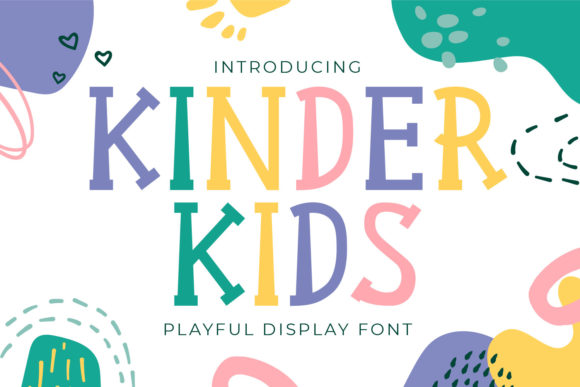
Kinder Kids
Review Completo da Fonte “Kinder Kids”: A Escolha Perfeita para Projetos Infantiles
Se você está procurando uma tipografia que transmita diversão, alegria e cuteness, a Kinder Kids chega como a solução ideal. Desenvolvida para ser playful e cute, essa fonte display se destaca em projetos que envolvem cartoons, jogos infantis e qualquer criação que precise de um toque delicado e encantador.
Principais Características da Kinder Kids
- Design divertido e amigável – Cada letra possui traços arredondados e espaçados, facilitando a leitura para crianças.
- Versatilidade – Ideal para capas de livros infantis, interfaces de jogos, convites de festas e materiais de marketing voltados ao público infantil.
- Alta legibilidade – Apesar do estilo lúdico, a fonte mantém clareza mesmo em tamanhos pequenos.
Por que escolher a Kinder Kids?
Ao escolher a Kinder Kids, você garante:
- Um visual cativante que atrai a atenção de crianças e pais.
- Coerência visual em toda a identidade visual de produtos voltados ao público infantil.
- Facilidade de integração em layouts digitais e impressos, reduzindo tempo de produção.
Aplicações Práticas
- Design de capas de livros de histórias para crianças.
- Elementos de UI/UX em aplicativos educativos e jogos mobile.
- Convites de aniversário, flyers e materiais promocionais de escolas.
- Postagens em redes sociais que buscam um toque alegre e descontraído.
A fonte Kinder Kids é mais do que apenas um estilo tipográfico; é uma ferramenta estratégica para quem deseja comunicar encanto e diversão em projetos infantis. Seu design cute e altamente legível a torna uma escolha segura e criativa, elevando a qualidade visual de qualquer peça que exija um toque carinhoso.